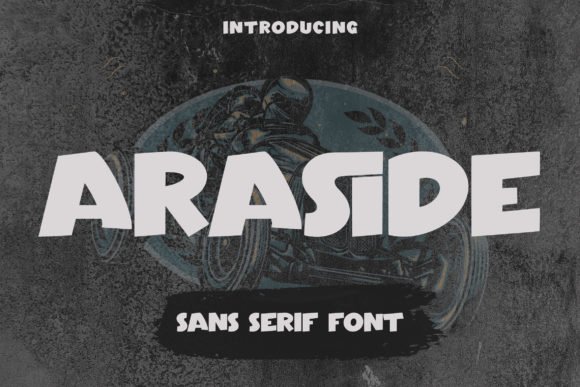
Araside - это крутой, смелый и модный шрифт.
Если вы используете его для дизайна, связанного с мультфильмами, детскими играми или просто для любого творения, требующего милых штрихов, этот шрифт станет отличным выбором.